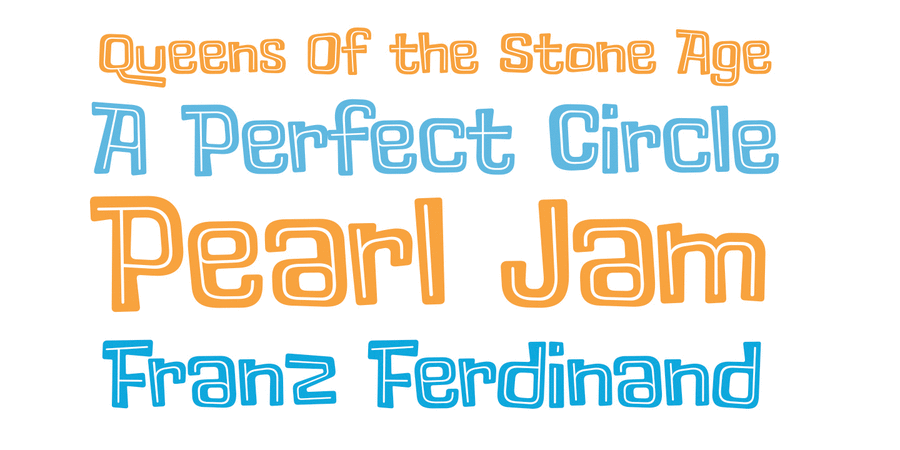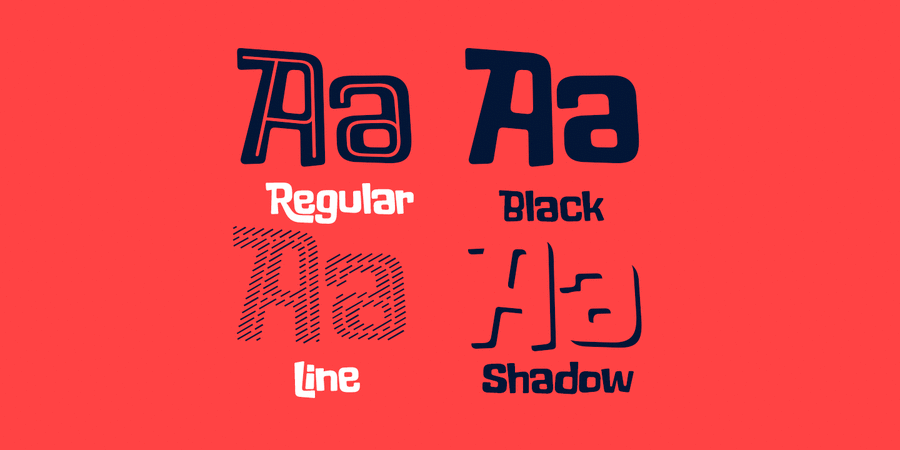
Lolapeluza (4 шрифта)
Шрифт вдохновлен логотипом фестиваля «Lollapalooza». Идея в том, чтобы создать веселый развлекательный шрифт. Лолапелуза идеально работает в дизайне продукции для детей и молодежи. Семейство состоит из 4-х начертаний: Regular, Black, Shaddow и Line. Лолапелуза может использоваться в качестве многослойного шрифта. Содержит кириллицу и набор альтернативных глифов. Шрифт разработан Родриго Арая Саласом и Гектором Барросо в 2015 году.
Lollapalooza